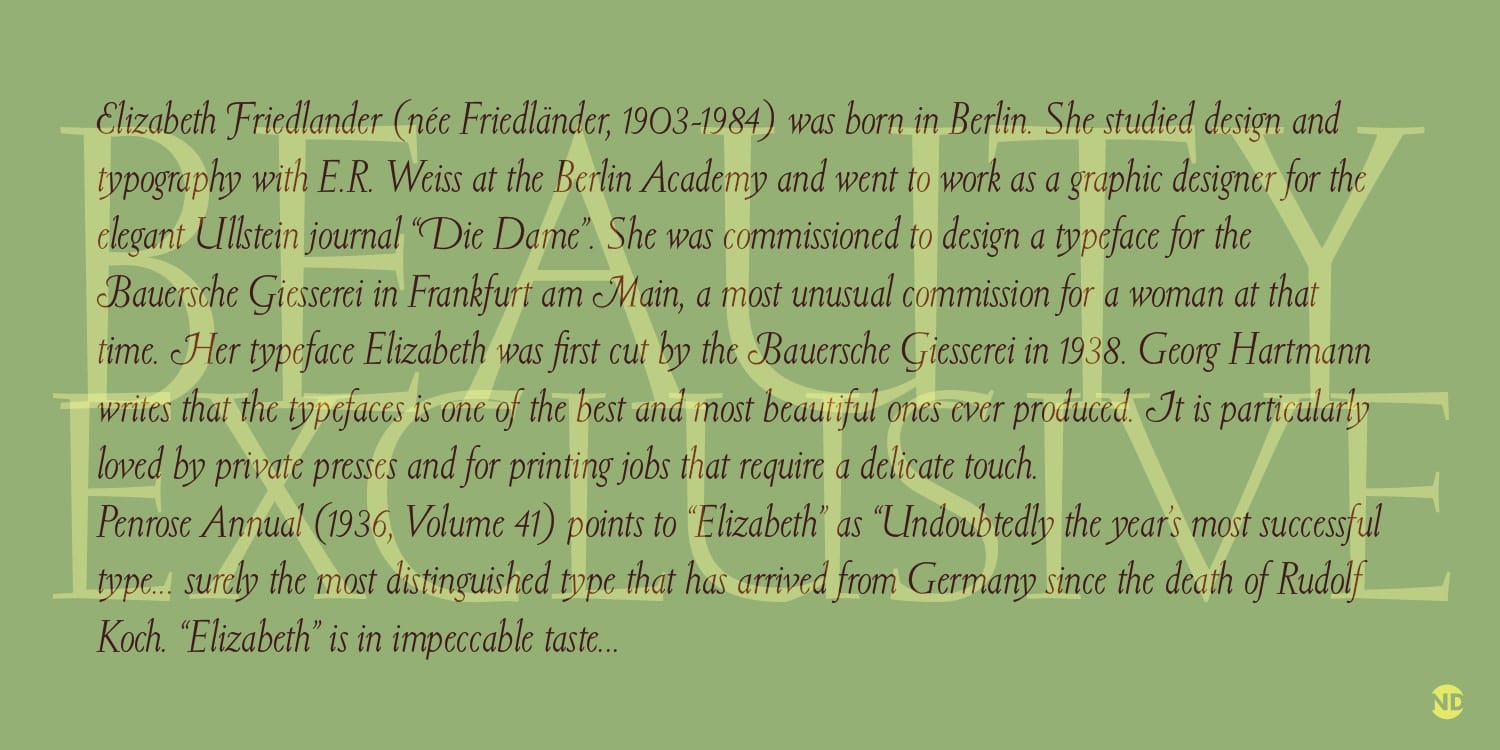
Elizabeth Friedlander. Una tipógrafa, calígrafa y diseñadora que trabajó con valentía en tiempos especialmente difíciles.
Elizabeth Friedlander nació en Berlin, donde estudió diseño, caligrafía y tipografía en la Academia de Bellas Artes. Fue diseñadora gráfica para la revista Die Dame, a cargo de los diseños de títulos y composición. Su sensibilidad y calidad gráfica hizo que La Bauersche Giesserei (antecesora de Bauer Types) le encargara el diseño de una tipografía, algo inusual para una mujer en aquellos tiempos. En 1938, su tipografía “Elizabeth” fue lanzada por La Bauersche Giesserei.
“La tipografía Elizabeth es uno de los mejores y más bellos tipos jamás producidos.” Georg Hartmann
Georg Hartmann escribió que el tipo Elizabeth es uno de los mejores y más bellos jamás producidos. Es particularmente apreciado por las prensas privadas y para impresos que requieren un toque delicado. En Penrose Annual de 1936 destacaron que la Elizabeth fue el tipo de mayor éxito del año. Probablemente el tipo más distinguido que llegó de Alemania desde la muerte de Rudolf Koch. Es de un gusto intachable… Veremos que libros que llegarán de Alemania nos mostrarán que un tipo más se añade a la más exclusiva de todas las clasificaciones tipográficas: el buen tipo de texto.
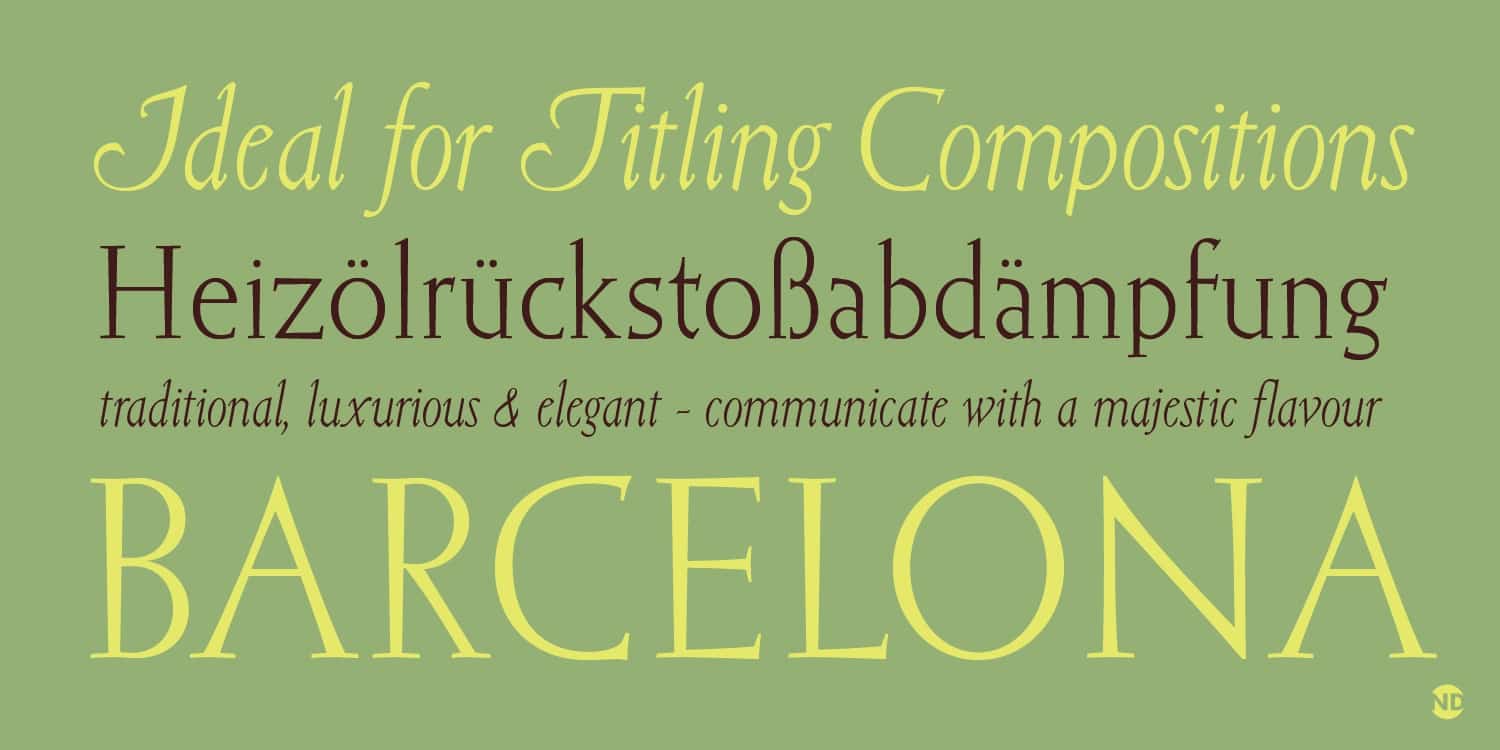
En octubre de 1936 debido a las regulaciones nazis, se trasladó a Milán y trabajó para la editorial Mondadori y para Editoriale Domus, además de desarrollar cubiertas de libros y publicidad. En 1939 consiguió trasladarse a Londres con un permiso del Servicio Doméstico que le permitió trabajar como empleada en este sector. Al poco tiempo consiguió adquirir fama como ilustradora y diseñadora. En junio 1948 recibe una carta de Jan Tschichold, asesor de Penguin Books. “Ignoro si conoce mi nombre como diseñador de caracteres y de tipografía, pero yo conozco su nombre. Me encanta su Elizabeth, especialmente la itálica. Me encantaría que colaborara con Penguin Books”. De este modo empezó a diseñar cubiertas para la editorial, adquierendo pronto relevancia en la profesión. Estrechó lazos con Hans Peter Schmoller, sucesor de Tschichold en Penguin Books, así como con William Morris de Monotype, para cuya empresa crea arabescos.
En 1961 se traslada a Irlanda, donde continua diseñando catálogos, mapas de caligrafía, exlibris,… así como las letras de los proverbios irlandeses en el pergamino. Fallece en este país en 1984.
En 2005 el diseñador y tipógrafo español Andreu Balius recibió encargo de Bauer Types (sucesora de Bauersche Giesserei) de digitalizar la Elizabeth. «Más que una digitalización se trata de un revival» nos cuenta Andreu Balius.
«Los diseños de Elizabeth que fueron concebidos para la fabricación de tipos móviles para impresión, por lo que supuso mucho trabajo de interpretación. Apenas pude contar con material impreso. Y los diseños de Friedlander variaban en función del cuerpo, por lo que tuve que tomar decisiones acerca de qué valores formales habría que mantener y resaltar, para conseguir un resultado elegante y bello. Por otra parte, y para ser fiel al trabajo de Friedlander, investigué sobre su vida, su trabajo y quienes fueron sus maestros. Ello me permitió poder entender mejor su diseño y, así, poder interpretar aquellas partes de su trabajo que me resultaban “conflictivas”. En definitiva, pude tomar las decisiones adecuadas, según mi criterio».
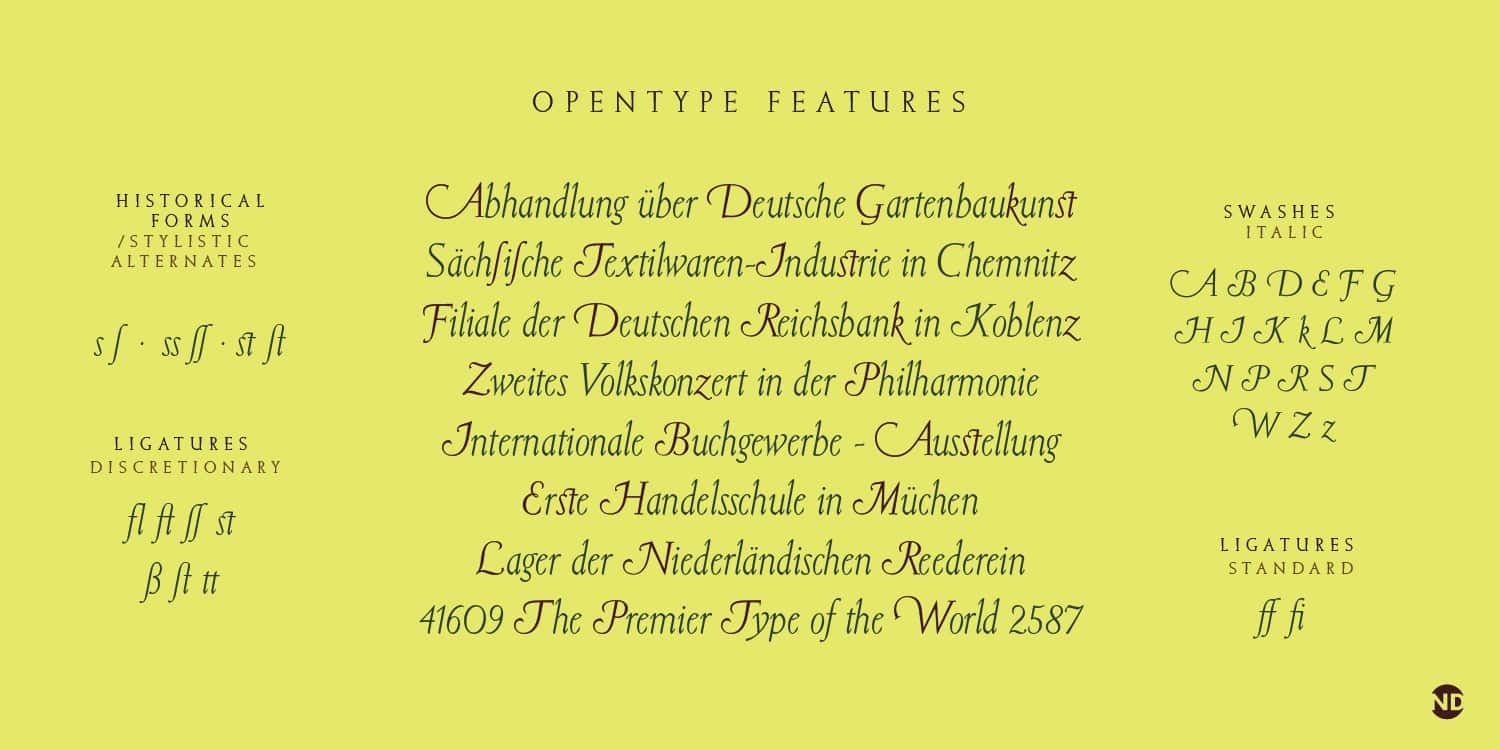
Elizabeth ND es una tipografía que consta de dos estilos: roman e italic en formato Open Type. Su set de mayúsculas swash de la itálica, enriquecen sus posibilidades de composición, convirtiéndola en una opción idónea para display/títulos. Asimismo las ligaduras discrecionales responden a este mismo carácter ornamental de la tipografía. Acorde a la época de su creación Elizabeth ND consta de la “s” larga y las correspondientes ligaduras derivadas. Con todo este conjunto de posibilidades y la influencia caligráfica en su apariencia. Elizabeth ND combina la elegancia y belleza, siendo una tipografía display idónea para cualquier proyecto que requiera de la personalidad refinada y clásica que ésta transmite.